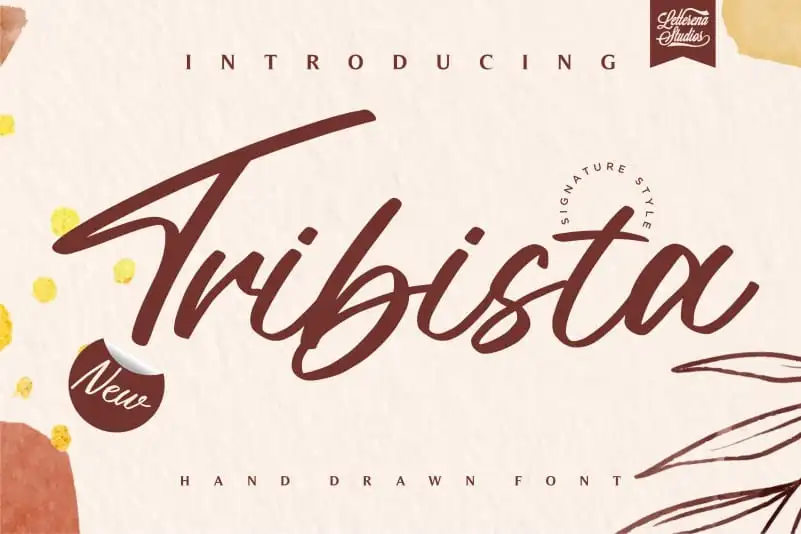
A fonte “Tribista Handwritten Font” é perfeita para quem busca uma fonte handwritten que transmite um toque natural e pessoal ao seu design. Conhecida por sua elegância e simplicidade, ela foi criada pelo designer letterenastudios. Esta fonte personalizada, disponível apenas para uso pessoal (sem fins comerciais), oferece uma sensação amigável e confiante que se encaixa perfeitamente em textos de marketing, design gráfico ou criação de identidade visual. Com sua tipografia handwritten única, cada projeto ganha um ar inconfundível e atraente. Atributos como essa são o sinal inequívoco de quem criou esta fonte, garantindo uma identidade visual forte que é perfeitamente compatível com qualquer projeto gráfico ou publicitário. Com “Tribista Handwritten Font”, você pode expressar seu estilo de forma única e elegante, sem dúvida um recurso valioso para designers e criadores de conteúdo.